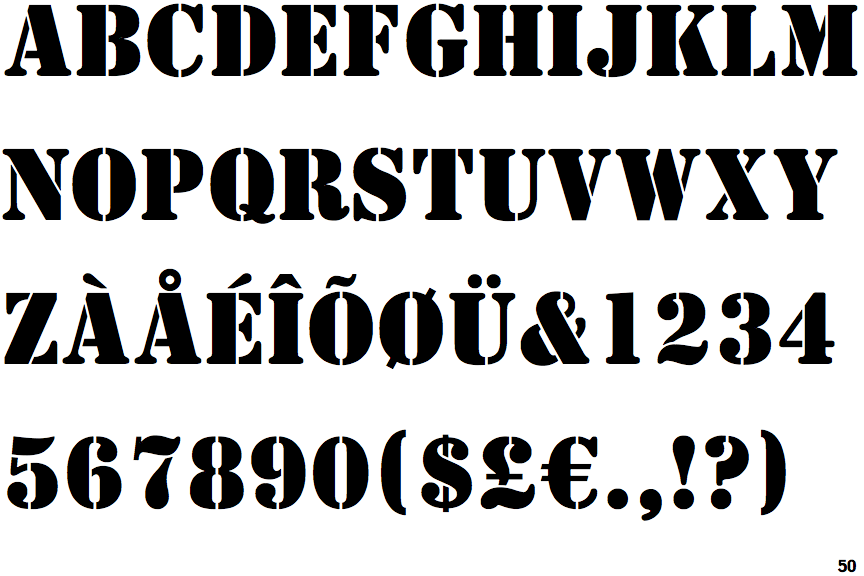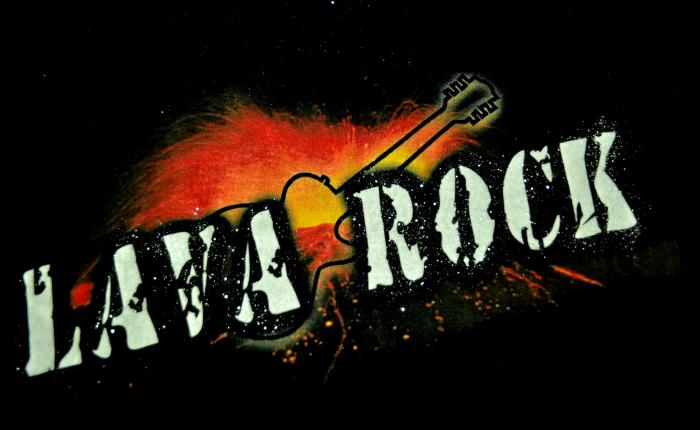
Hallo ich suche nach dieser Schrift wenigstens aber sehr,sehr ähnlich.
Es ist für unseren Verein, der Macher dieses Schriftzuges ist nicht mehr erreichbar ( nicht mehr bekannt) und ein Original gibt es nicht.
Die Basis war wahrscheinlich eine Stencil (Gerry Powell, 1937). :tutor:  Diese basiert auf der Clarendon und entspricht in etwa einigen der Schablonenschriften der US-Army auf Fahrzeugen und Ausrüstung.
Typeface: Stencil (BT)
Designer: Gerry Powell
Year: 1937
Publisher: Bitstream
No lower-case characters.
Diese wurde dann misshandelt. :neenee: Säurebad, Schleifscheibe, Waterboarding, ... Jaja, die Welt ist voller Grausamkeiten ... Es ist aber durchaus möglich, das es sich hier nur um einen bedauerlichen Einzelfall gehandelt hat und es keine komplette Schrift dahinter gibt. Aber Verbrechen dieser Art sind sehr weit verbreitet und werden von einigen Tätern offen zur Schau gestellt, ja sogar gegen Geld verkauft.
4YEOstamp heißt sie, free for personal use.